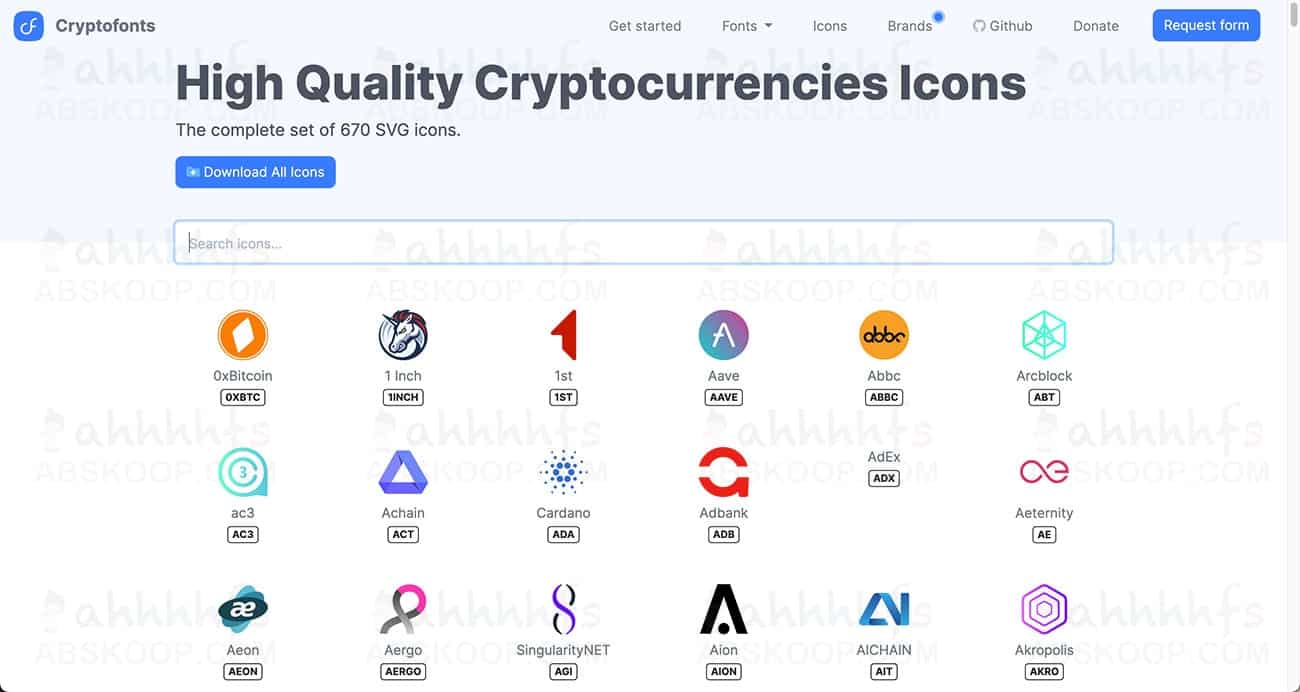
670款加密货币SVG图标集:提供全平台兼容的免费字体化矢量资源
CryptoFont 为开发者和设计师提供了一套专业且免费的加密货币图标库,涵盖了海量的 SVG 矢量图与网络字体图标,是构建区块链相关界面时的理想资源站。
670 款加密货币 SVG 图标集:提供全平台兼容的免费字体化矢量资源
适用场景
这些图标非常适合用于加密货币交易所界面、数字钱包 App、区块链项目官网以及任何需要展示主流或新兴代币标识的 UI 设计场景。